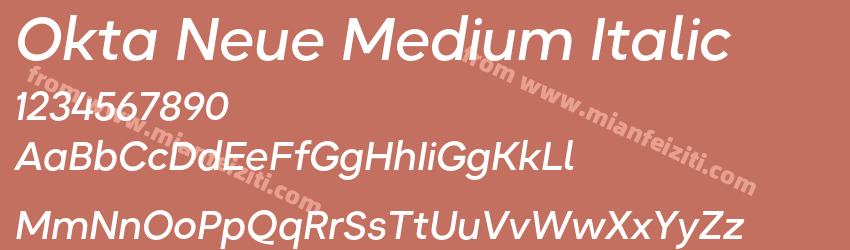
Okta Neue Medium Italic
字体名称: Okta Neue Medium Italic
Postscript名称: OktaNeue-MediumItalic
本款“Okta Neue Medium Italic”是一款书写很新颖的字体,字体大方,适合各种设计作品使用!欢迎下载!